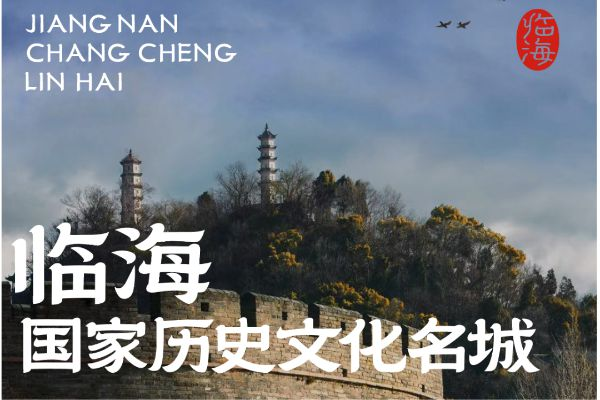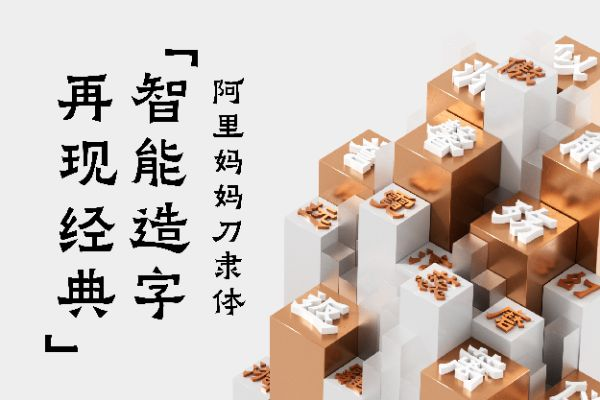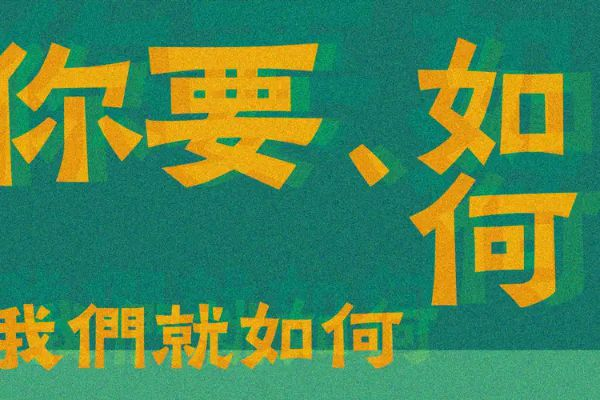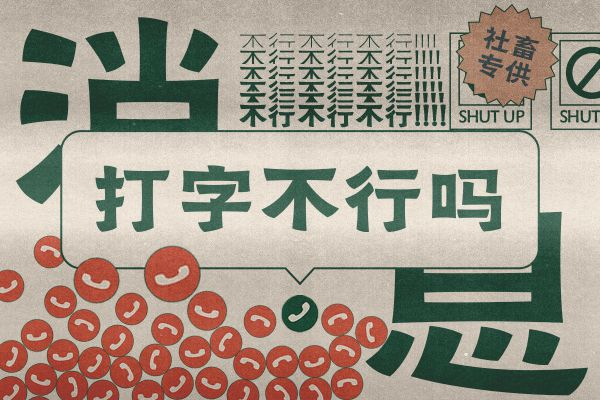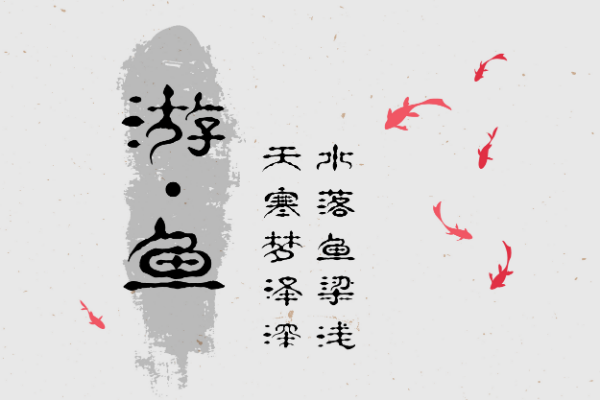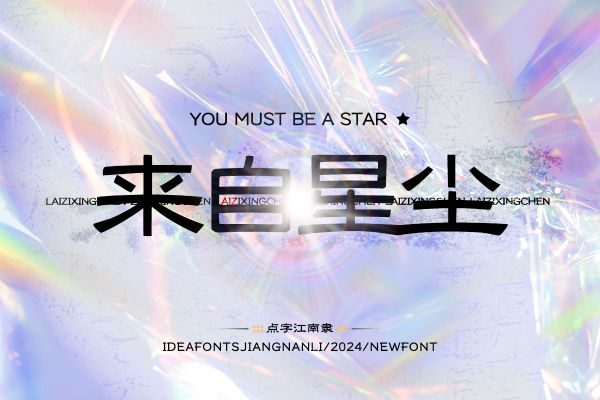
免费商用的隶书字体去哪下载?分享一款神器给你
隶书在做传统文化、餐饮或者是中式LOGO时真的无可替代,很多做设计的同学都会问,免费商用的隶书字体去哪下载?才能既省钱又安心?今天推荐给大家一款工具,字由,带大家看看怎么通过字由快速搞定免费商用的隶书字体。
三、免费商用的隶书字体推荐
1. 临海隶书
临海隶书是一款传统风格的隶书字体。这款字体保留了隶书典型的"蚕头燕尾"特征,笔画舒展、横平竖直,具有古朴典雅的韵味。适合用于标题设计、文化类海报、传统节日宣传等需要展现中国传统文化气息的场景。
1. 阿里妈妈刀隶体
阿里妈妈刀隶体是阿里巴巴旗下阿里妈妈团队推出的一款创新隶书字体。它在传统隶书的基础上融入了现代设计理念,笔画更具力量感和锋利感,如同刀刻般刚劲有力。字形结构简洁明快,既保留了隶书的横向舒展特点,又增加了现代感和视觉冲击力。
四、低成本隶书字体推荐
会员隶书字体推荐
1. 点字金刚隶
点字金刚隶是一款笔画厚重、结构稳固的隶书字体。"金刚"之名体现了其刚劲有力的特点,笔画粗壮饱满,横画舒展、竖画挺拔,整体气势磅礴。字形端庄大气,具有强烈的视觉冲击力和力量感。适合用于需要突出份量感的场景,如标题设计、品牌标识、文化海报等。
1. 点字清逸隶
点字清逸隶是一款笔画清秀、风格飘逸的隶书字体。相比传统隶书的厚重感,清逸隶更注重线条的灵动和优雅,笔画适中偏细,结构疏朗有致,呈现出清新脱俗的气质。
1. 汉仪珍珠隶
汉仪珍珠隶是汉仪字库推出的一款精致隶书字体。整体风格柔和亲切,既保留了隶书的横向舒展特点,又增添了几分现代感和可读性。适合商业包装、品牌设计、广告文案等需要兼顾传统与现代感的场景。
1. 点字江南隶
点字江南隶是一款带有江南文化气息的隶书字体。字体笔画秀丽流畅,结构含蓄内敛,透露出江南水乡的温婉气质。适合江南主题设计、旅游文化宣传、茶文化、园林景观等需要体现南方文化韵味的应用。
1. 点字青花隶
点字青花隶是一款融入青花瓷元素灵感的隶书字体。这款字体在设计上汲取了青花瓷的雅致与古朴,笔画流畅自然,字形端庄秀美,具有浓郁的东方美学意境。
五、 我使用隶书的常用场景
• 主标题:四个字或者六个字的标题。隶书那种左右舒展的笔画,能瞬间压住整个画面的气场。
• 印章或落款:在画面的角落,放一个红色的印章效果,里面用隶书写上品牌名,那种文化底蕴立马就上来了。
• 短句装饰:比如一两句非常有情怀的文案,用隶书斜着放或者错落排布,很有艺术感。